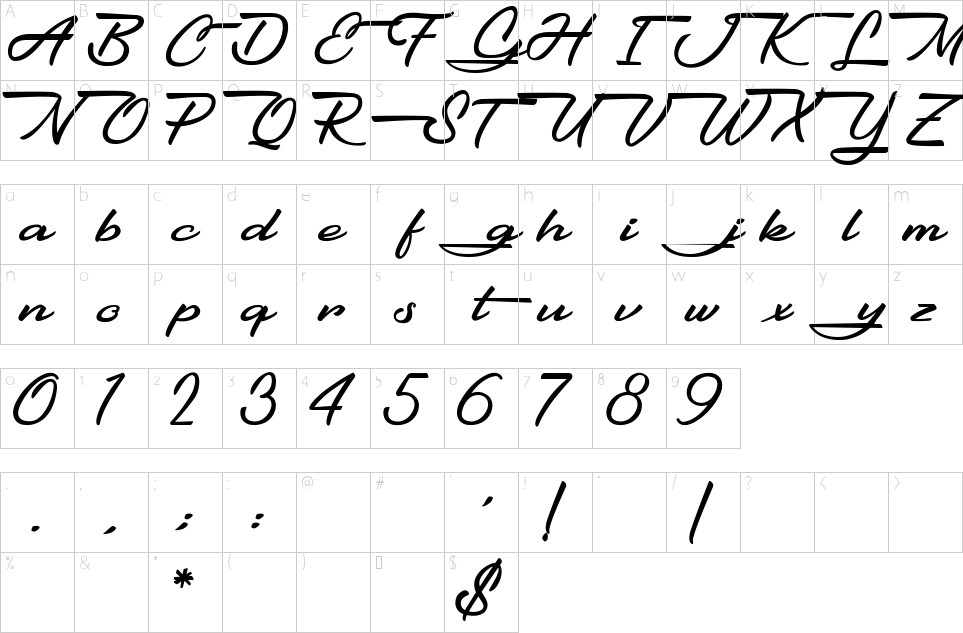
Gentlemanly Font
A Gentlemanly Font oferece uma escrita elegante e sofisticada perfeita para projetos que valorizam beleza e refinamento. Desenvolvida pelo Octotype, a Gentlemanly é conhecida por sua facilidade de uso no Windows e Mac sistemas operacionais. Com linhas curvas suaves e graças a uma tipografia cuidadosamente projetada, esta fonte garante um layout profissional em qualquer projeto que você decida fazer. A versão gratuita da Gentlemanly Font é um excelente exemplo dos recursos gráficos de alta qualidade que os designers estão sempre procurando. Com seu design minimalista e moderno, a Gentlemanly é uma escolha inteligente para quem busca uma fonte elegante sem comprometer a legibilidade. Agrade-se ao Octotype pelo lançamento desta fonte gratuita, tão bela quanto funcional.
Mapa de caracteres da fonte Gentlemanly Font